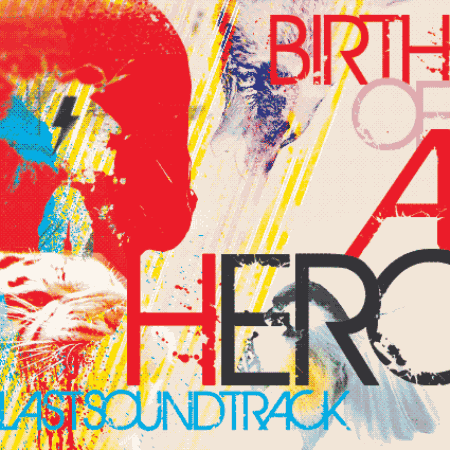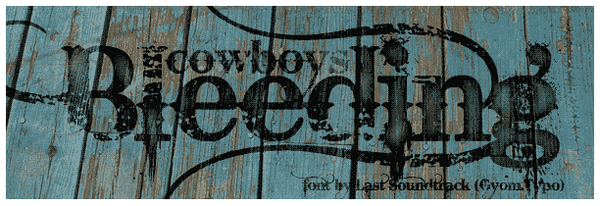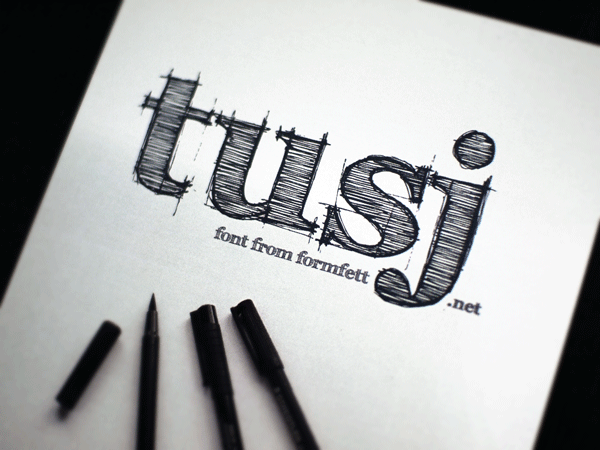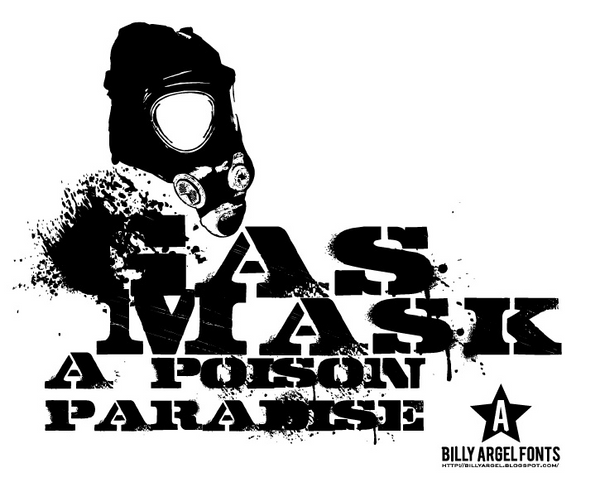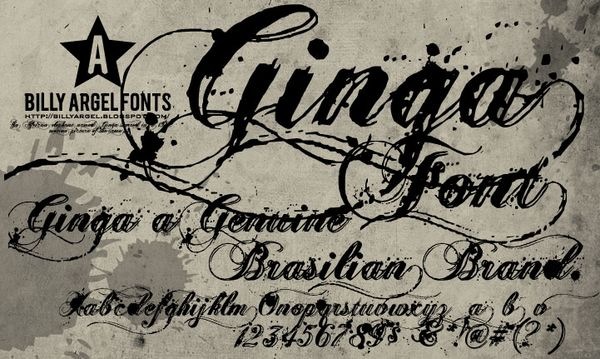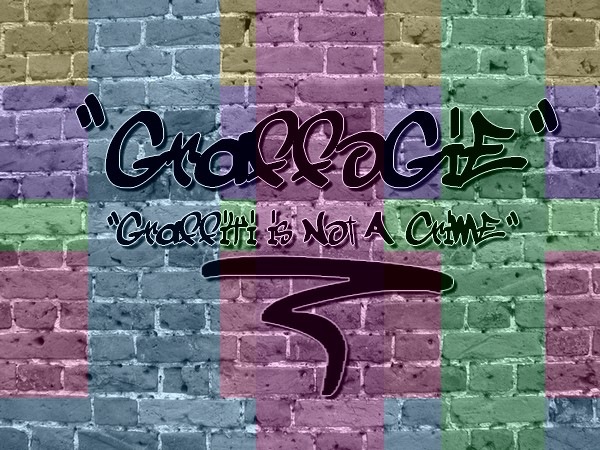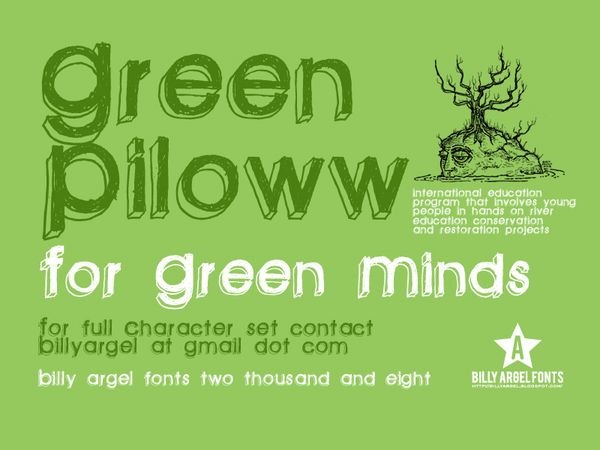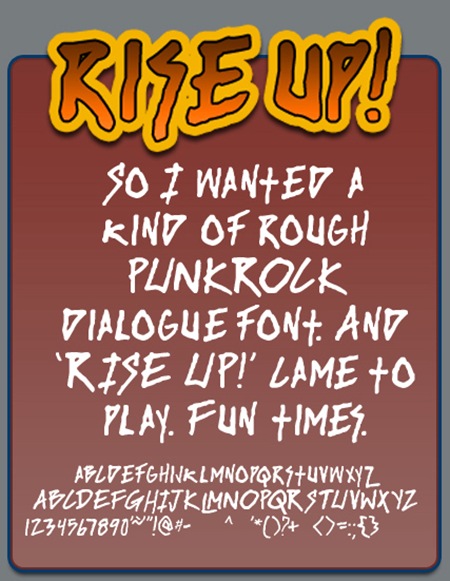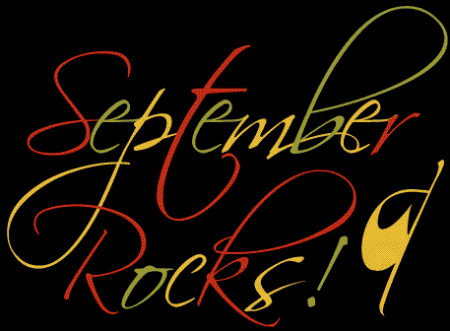
Стильные латинские шрифты-2
латинские-шрифты-2В сети можно найти множество шрифтов, но за них в большинстве приходиться платить. В этой подборке вы найдете ещё 10 различных шрифтов которые в дальнейшем смогут вам помочь при создании ваших дизайнов. Все шрифты бесплатны и ссылки с изображений ведут к зип папке с шрифтом. Первую часть подборке вы сможете увидеть в ранее опубликованной статье Стильные латинские шрифты.
Шрифт под названием “Birth of a Hero”
Шрифт “Rise Up”
Шрифт “Scriptina”
Шрифт “Bleeding Cowboys” который вы могли уже видеть в другой подборке. Тут ссылка с него ведет сразу к зип папке с этим шрифтом.
Заштрихованный шрифт “FFF Tusj”
Стильный шрифт “Gasmask”
Шрифт “Ginga” в стиле гранж
Шрифт-графити “Graffogie”
Шрифт от руки “Green Piloww”
Шрифт “Sidewalk”